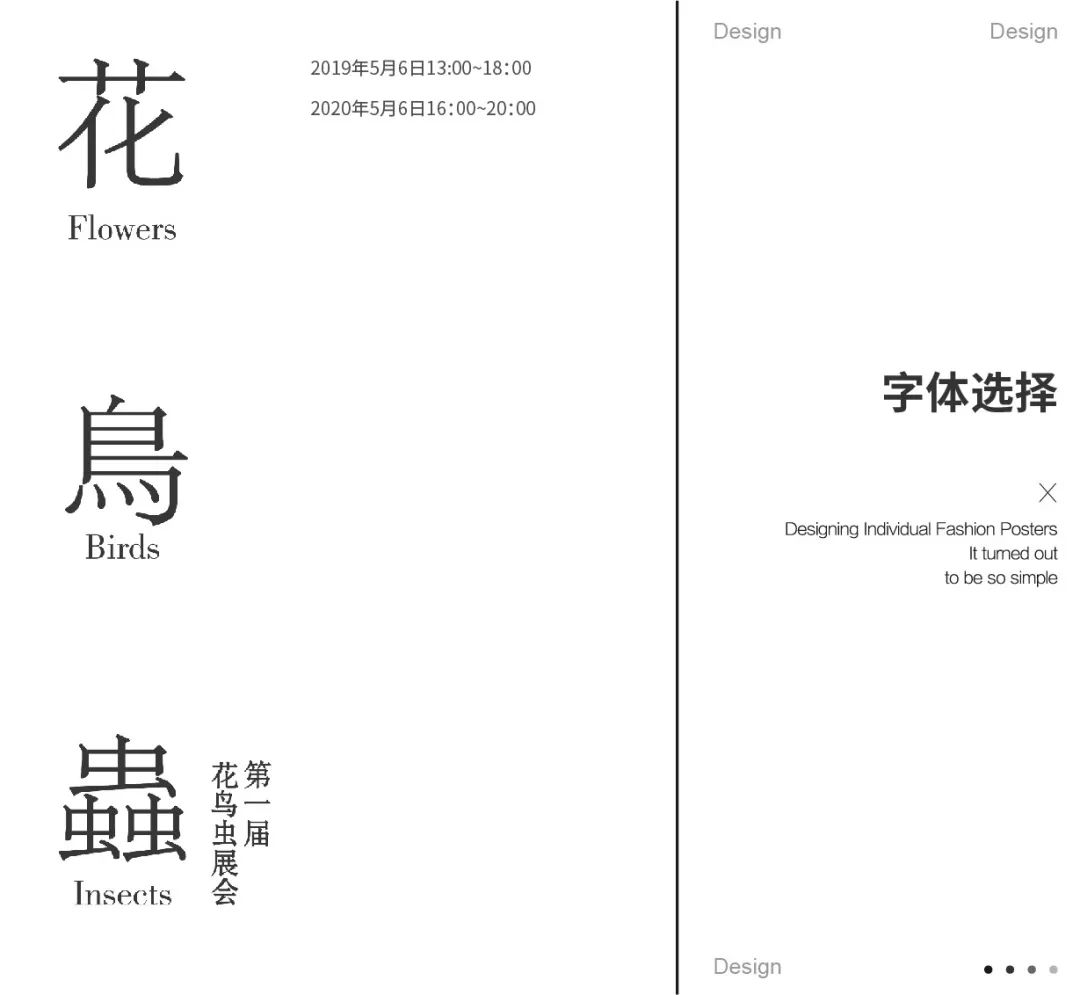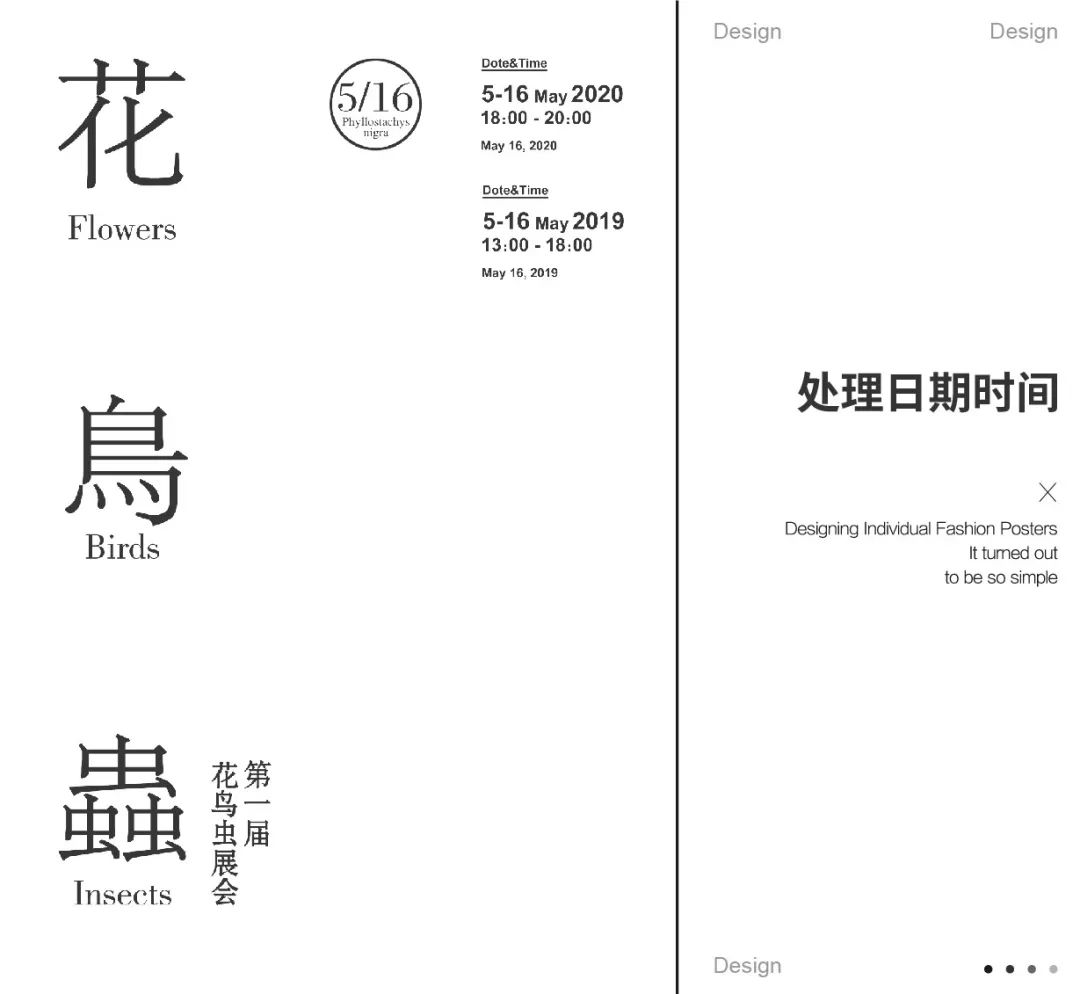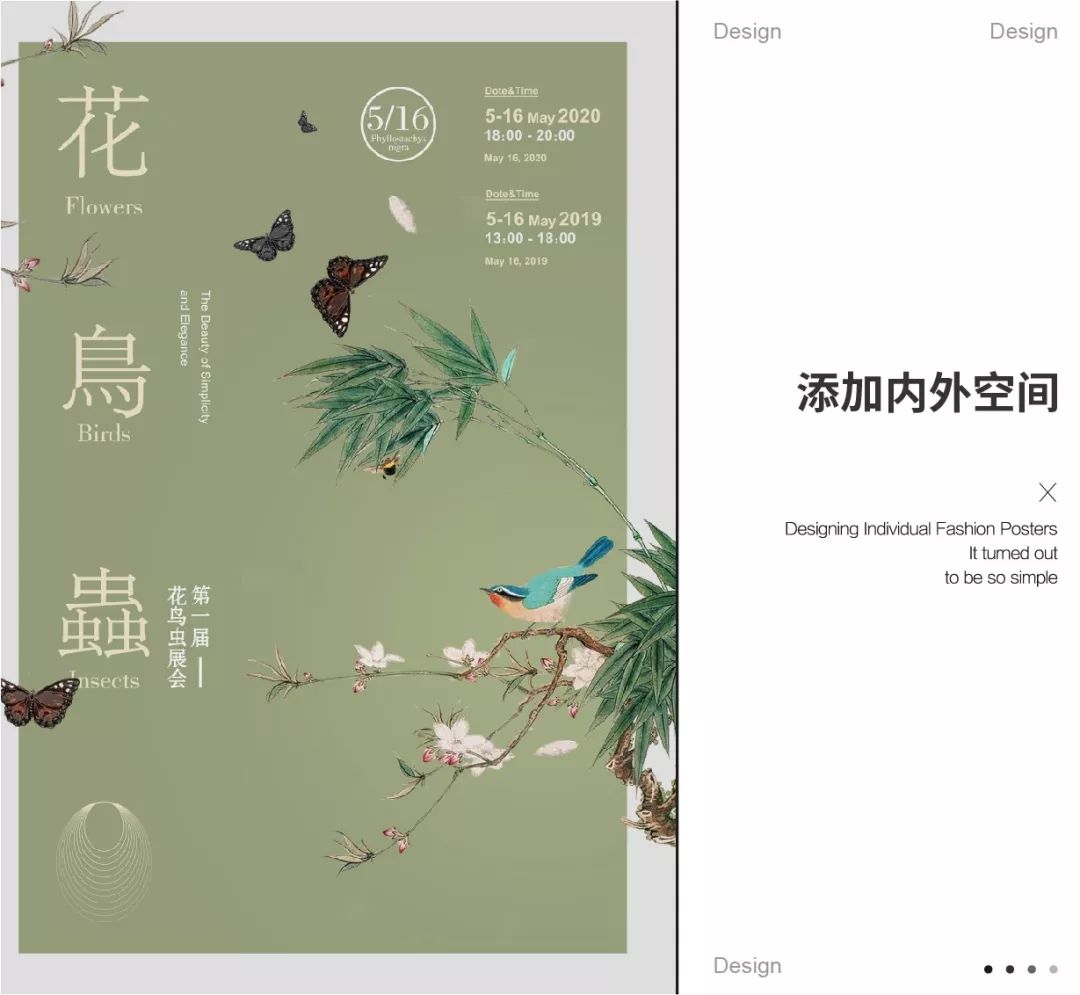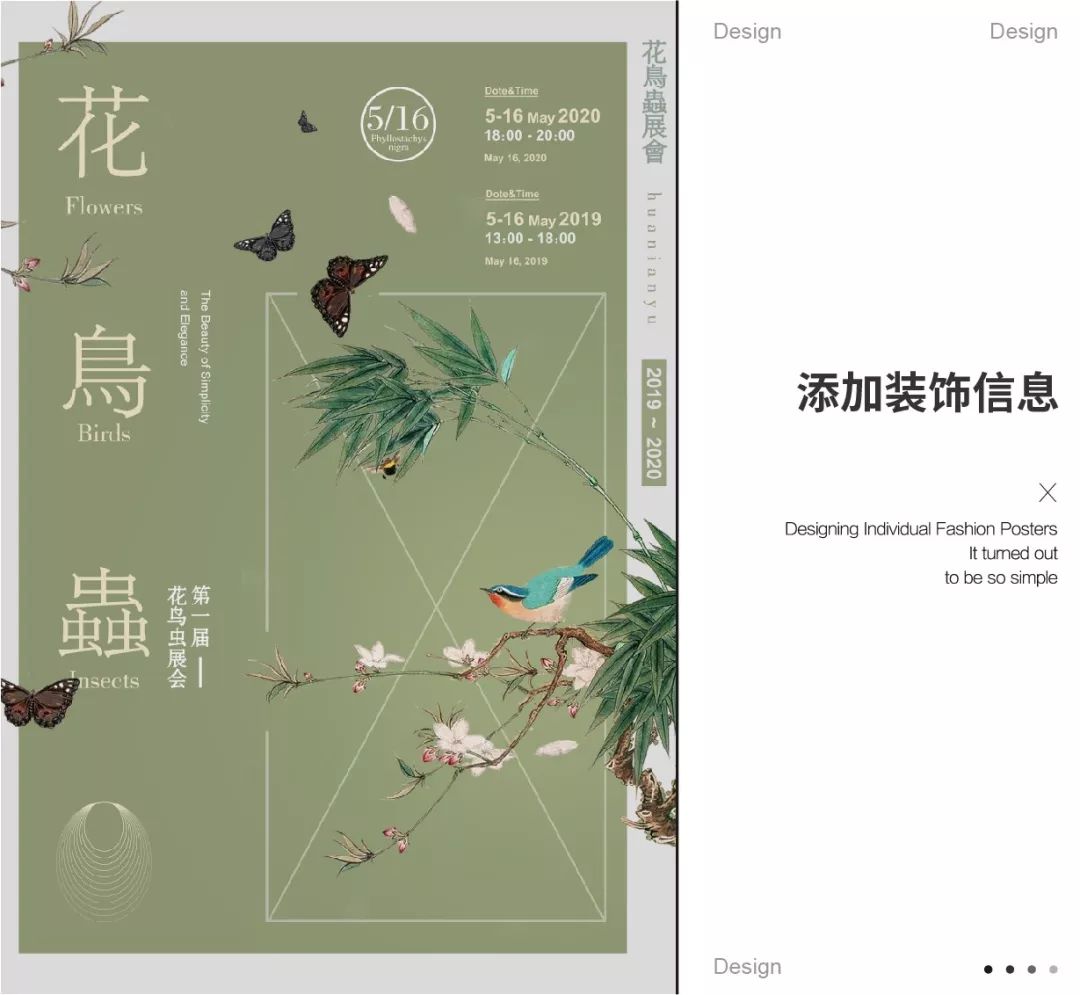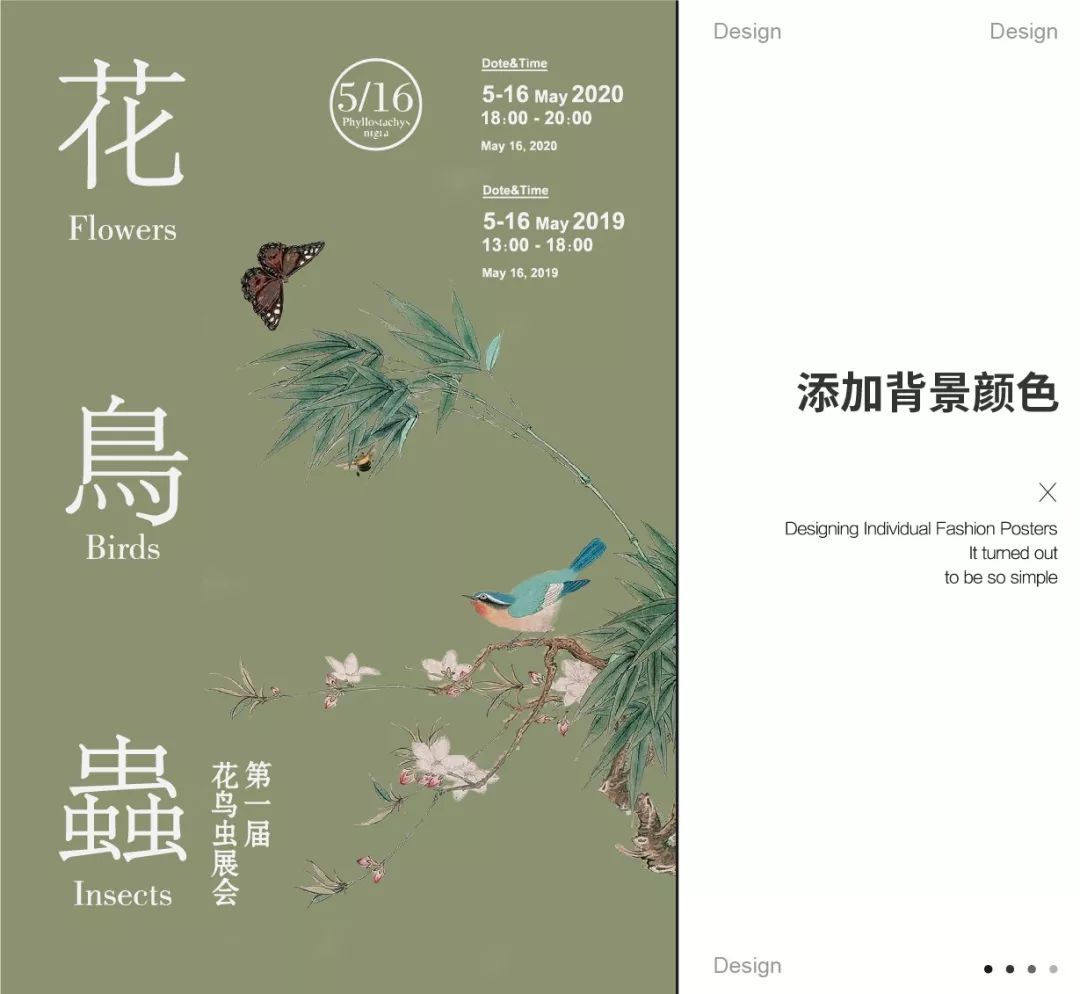
你知道海报的完整设计思路吗?一起来学习下海报设计的完整思路
今天给大家带来的是一个展会类型的海报,大家可以学习一下这样的海报思路,我们以后可能也会遇到这类的项目,提前学习一下设计的思路可以有效帮助大家在工作中快速设计。大家在平时的设计过程遇到了什么难以解决的问题可以直接私聊发到我的公众号里,如果大家都为一个问题感到困惑我也会专门出一篇文章或者视频帮助大家解决问题,提升设计水平,闲话不多说,下面会通过一个实际的项目去我们开始今天的案例演示。
本期给大家带来的是一份展会海报的设计思路,我们一起来看看如何展开我们的设计。
展会类型海报设计的难点主要在于如何搭建稳定的版式,以及如何突出展会的重要信息。
突出展会信息我们首先知道需要突出哪一类的信息,通常来说这类项目的时间日期,主标题肯定是需要着重设计的,所用到的手法就是信息符号化。
搭建稳定的版式主要依托我们所学的构图的知识,或者网格系统来规范我们元素的放置,在版式的基础上想要稳定我们需要根据项目的气质选择合适的字体确认风格。
从这个美术展览的海报我们可以看到,整体的版式是非常舒服的对于信息层级也很到位。
同样我们也可以学习它的构图以及对于信息的符号化处理方式。
把海报拆分成线面的形式,可以帮助我们更好的看到设计的一些本质,更清晰的认识海报的结构。
画面整体使用的满版构图,整体的场景感打造的非常好,可以学习他对于字体的把握。
同样把海报拆分成线面的形式,分析海报。
通过阅读文案我们可以知道我们画面的表现倾向,整体需要表现的清新文艺,富有设计感。
通过信息的重要性分出信息的各个层级,确定信息在画面中的大小占比。
现在来解决版式的部分,整体选用了左右分割构图来规范我们的画面。
把文案先放在画面里。
根据空间分配文案。
简单处理主标题的间距,占据空间。
首先进行字体选择,主标题需要字形相对丰富的字体会更加合适,在这里使用的是一个繁宋的字形。
然后处理日期和时间的信息,注意信息的亲密性,也就是说要根据信息的属性进行距离的调整。
给画面添加主体,注意主体要符合我们的文案内容,一定要准确并且恰当。
刚才我们的背景还稍微有些单调,这一步添加背景的颜色来增强画面的视觉性。
使用内外空间的手法来继续强化视觉性,同时这样的手法也会使画面主体更加的突出明显。
通过添加一些装饰的小信息可以让画面更加的饱满。
最后做一个样机的效果,提升画面的质感。
>样机效果图<
最后总结 >
通过这个案例我们可以看出,设计并不是单一的文字编排,更不是纯粹的炫技,我们只需要简单的做好元素的协调,构图的选择,我们的画面就可以有一个非常好的效果了。希望大家看了这篇文章有所收获。